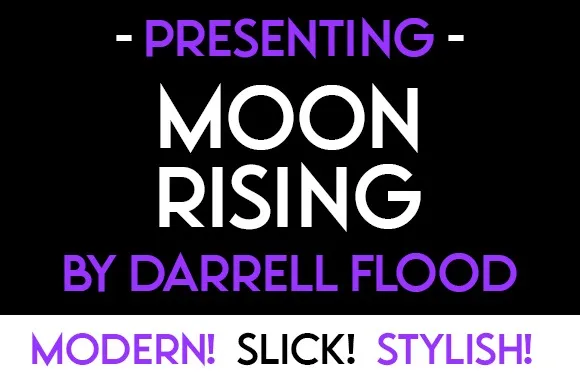
Moonrising Font – Download Grátis
Afont Moonrising é uma tipografia sans-serif geometrica que se destaca por seu estilo clean e legível, perfeito para qualquer projeto que exija facilidade de leitura e funcionalidade. Ela foi criada pelo designer Dadiomouse no site 99designs e compartilhada com o mundo da comunicação visual. Este tipo-fonte all-caps é especialmente apropriado para criações futuristas, designs relacionados à ciência e apresentações técnicas. Seja para um projeto de software ou uma revolução tecnológica em andamento, Moonrising atende perfeitamente às necessidades do seu trabalho. Engane-se se pensasse que era apenas um design puramente estético; Moonrising tem tudo o que você precisa para criar projetos de alto impacto e relevância no mundo moderno da informação visual.